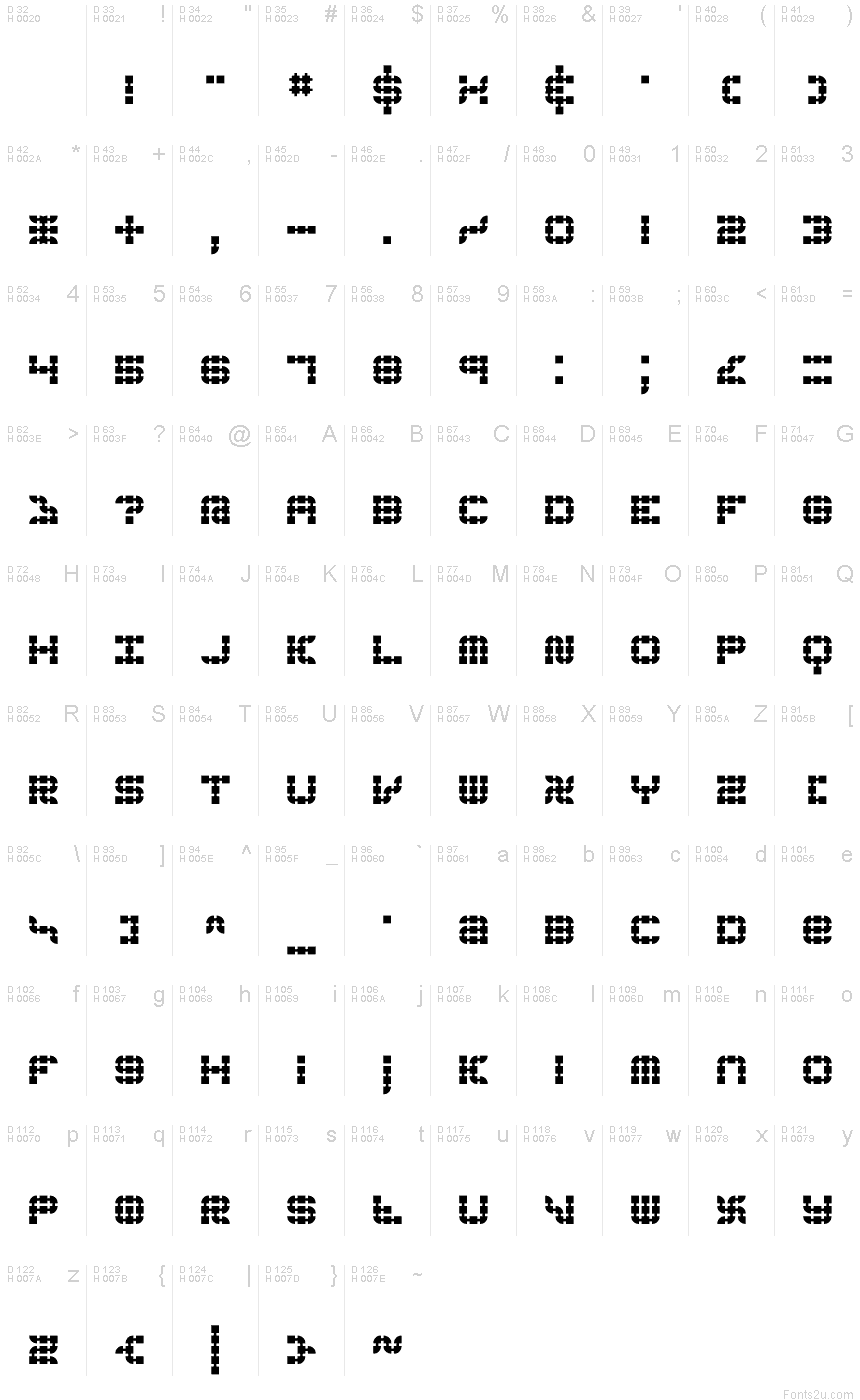
Konector od Aenigma Fonts to darmowy, dekoracyjny krój techno, który wygląda, jakby został złożony z masywnych cyfrowych klocków. Każda litera przypomina fragment płytki drukowanej: kwadratowe krzywe, blokowe segmenty i ostre, przypominające siatkę łączenia, które pasują do siebie z mechaniczną precyzją. Efekt jest wyrazisty, hałaśliwy i bezkompromisowo syntetyczny – idealny, gdy potrzebujesz typografii, która wygląda na zaprojektowaną, a nie narysowaną.
Dzięki Konector możesz wprowadzić plakaty sci-fi, ulotki EDM, tytuły gier, logotypy technologiczne, futurystyczne opakowania i identyfikatory eventowe w świat cybernetyki. Jego ciasny, modularny rytm sprawdza się świetnie w dużych rozmiarach, gdzie każdy detal „złącza” pozostaje wyraźny i czytelny. Ten darmowy font świetnie komponuje się z czystym bezszeryfowym krojem w tekście głównym, pozwalając Konector przejąć rolę głośnych, przyciągających wzrok nagłówków.
Konector (BRK)